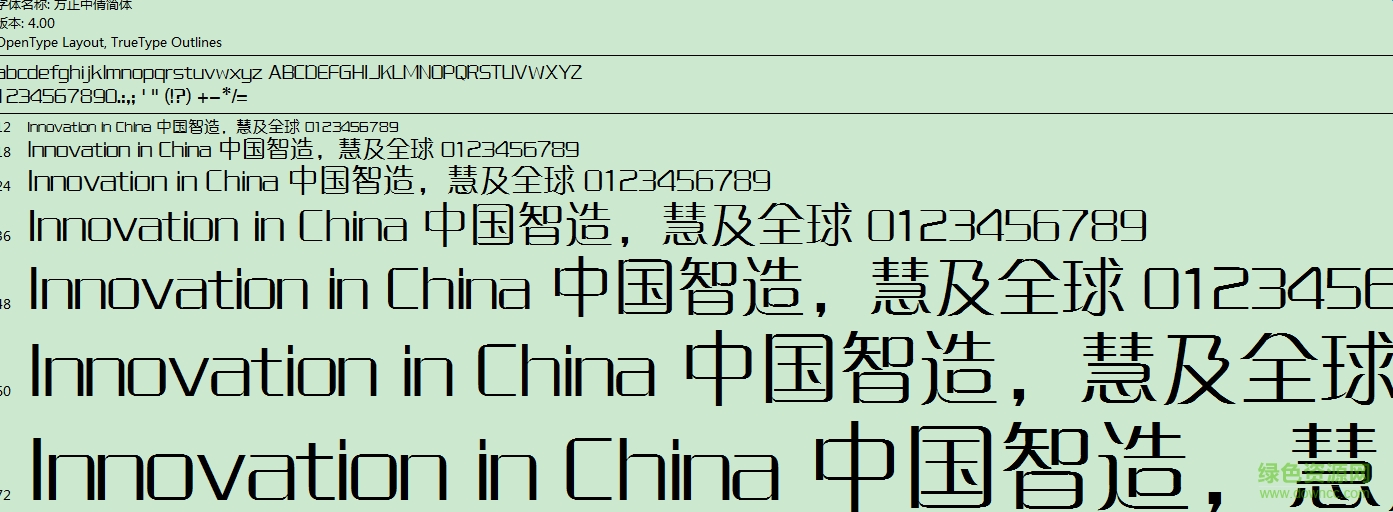
fzzqjw gb10字体是一款方正字体中非常专业字体的一种,这款字体也叫方正中倩体,用途非常广泛,有需要的就来绿色资源网下载吧!
fzzqjw gb10字体是很多朋友都在寻找的一款字体,小编为大家提供免费下载。字体边缘采用了艺术形态,更加耐看。做美工、艺术广告设计的朋友不要错过哟,快来绿色资源网踊跃下载吧!